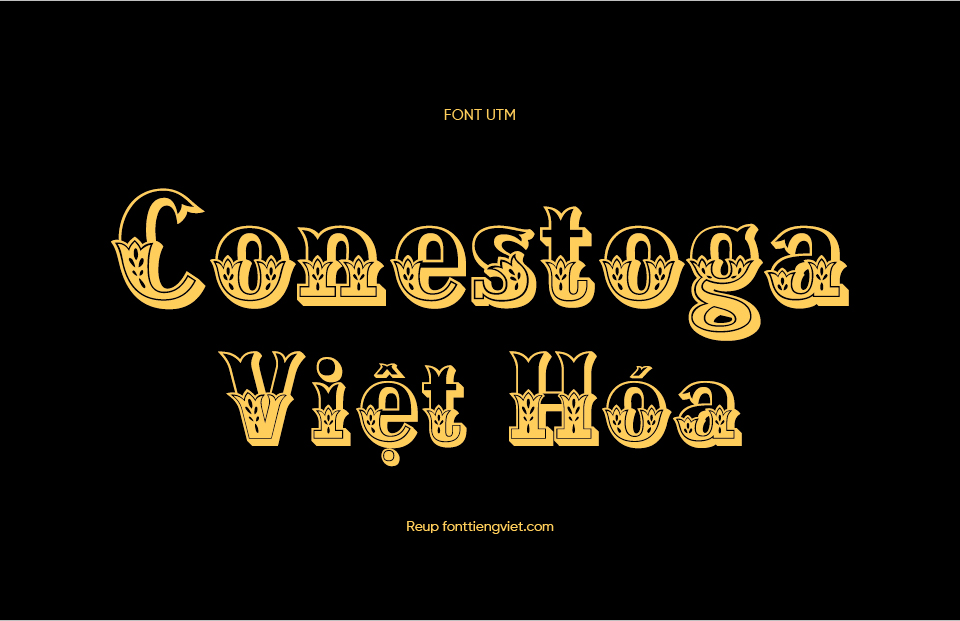
Font Việt hóa UTM Conestoga
Giới thiệu về bộ Font Việt hóa UTM Conestoga
Trong thế giới thiết kế đồ họa chuyên nghiệp, việc lựa chọn một Font Miễn Phí chất lượng luôn là ưu tiên hàng đầu của các designer. Font Việt hóa UTM Conestoga nổi lên như một giải pháp tuyệt vời nhờ phong cách mạnh mẽ, hiện đại và vô cùng linh hoạt. Đây là bộ phông chữ thuộc dòng UTM nổi tiếng, được tinh chỉnh tỉ mỉ để phù hợp hoàn toàn với bảng mã Unicode tiếng Việt, giúp người dùng không còn lo lắng về lỗi hiển thị ký tự đặc biệt hay dấu câu trong quá trình làm việc.
Đặc điểm nổi bật của phông chữ
Font Việt hóa UTM Conestoga sở hữu những đường nét cứng cáp nhưng không kém phần uyển chuyển, mang lại cảm giác tin cậy và chuyên nghiệp cho mọi ấn phẩm. Kiểu dáng chữ có độ tương phản vừa phải, giúp tăng khả năng đọc trên cả màn hình kỹ thuật số lẫn bản in truyền thống. Đặc biệt, bộ font này rất phù hợp để ứng dụng vào việc thiết kế tiêu đề sách, bìa tạp chí, hoặc các dự án nhận diện thương hiệu cho doanh nghiệp và trường học.
Ứng dụng thực tế của Font Việt hóa UTM Conestoga trong đời sống
Nhờ tính ứng dụng cao, Font Việt hóa UTM Conestoga thường xuyên xuất hiện trong các poster sự kiện, banner quảng cáo và cả trong các bài thuyết trình học đường. Đối với các bạn học sinh và giáo viên, việc sử dụng font chữ này sẽ giúp tài liệu giảng dạy trở nên sinh động và lôi cuốn hơn. Bạn có thể dễ dàng cài đặt và sử dụng nó trên các phần mềm phổ biến như Adobe Photoshop, Illustrator hay Microsoft Word để tạo ra những sản phẩm sáng tạo mang đậm dấu ấn cá nhân.